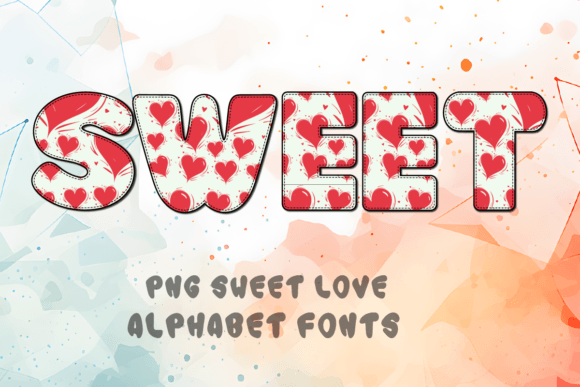
Sweet Love Alphabet Fonts
適切なデザイン要素を見つけるのは難しい場合がありますが、Sweet Love Alphabet Fontsは作品を即座に引き立てる優れたコレクションを提供します。
POD(オンデマンド印刷)製品、結婚式の招待状、またはソーシャルメディアのグラフィックを作成している場合でも、Sweet Love Alphabet Fontsは理想的です。